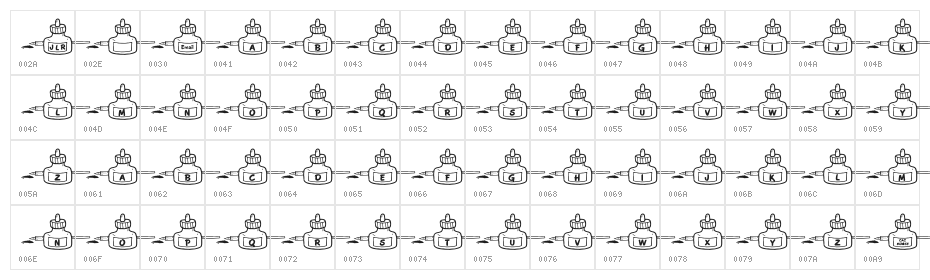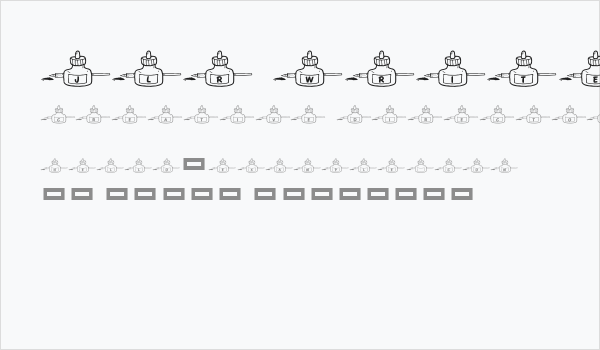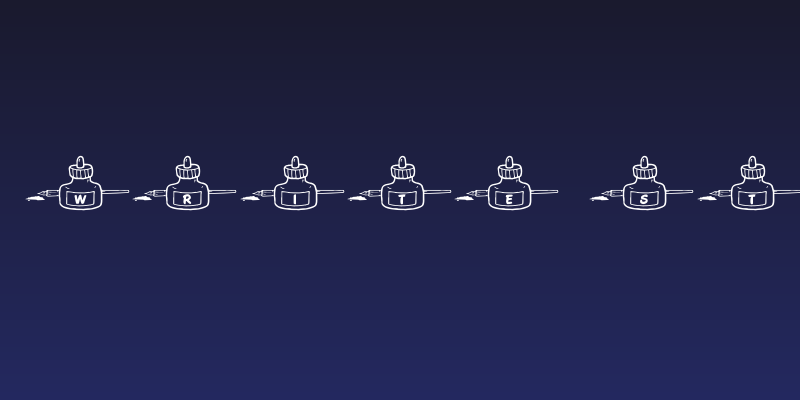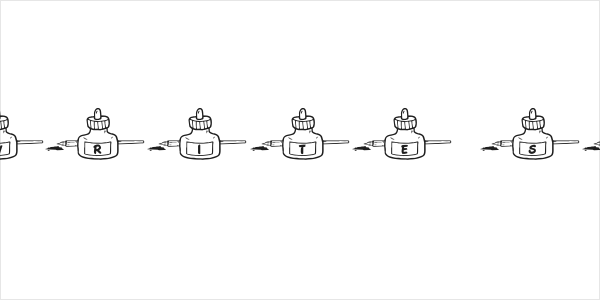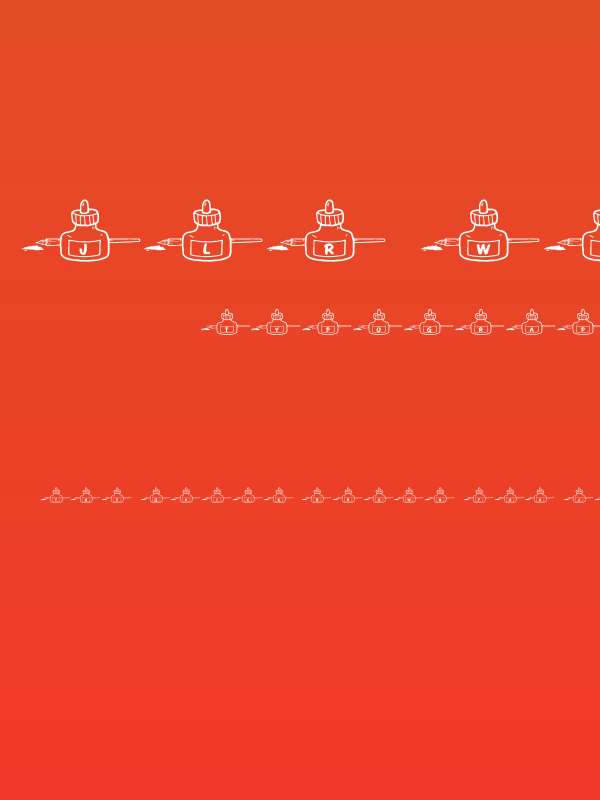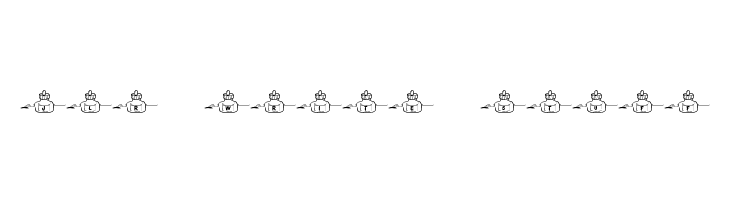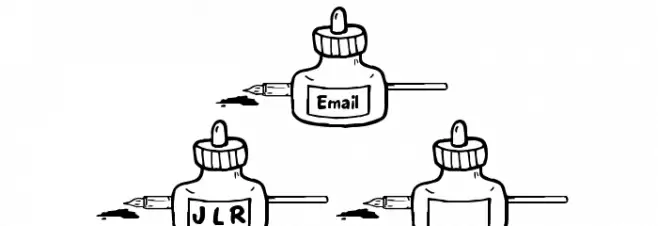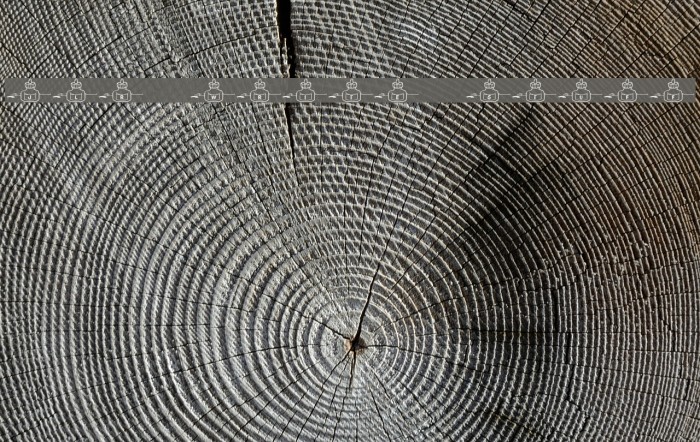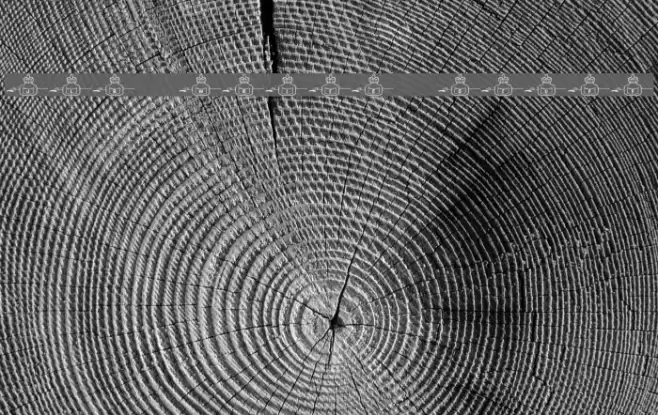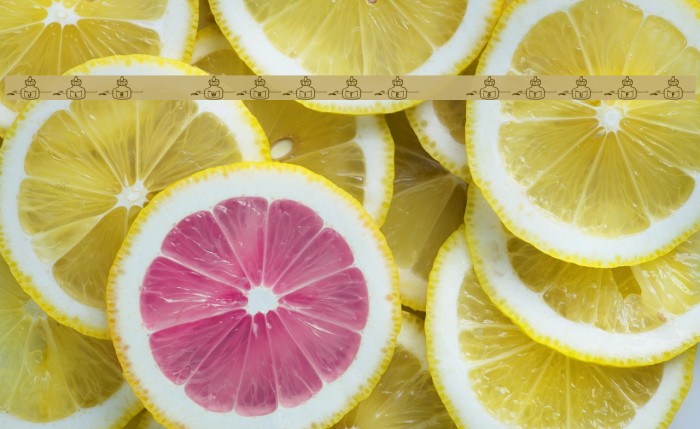
JLR Write Stuff Font
| Caso de uso | Logos, Artistic projects, Invitations |
| Proyectos propuestos | Ideal for creative projects such as greeting cards, invitations, artistic posters, or branding for artistic ventures. |